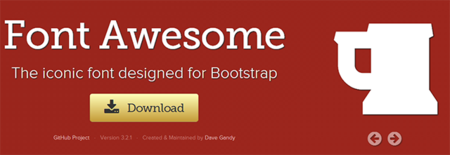
Cada vez más los diseñadores web queremos prescindir de las imágenes basadas en bits como png o jpg todo lo que podamos en favor de contenido vectorial y escalable. Con esta idea se ha creado Font Awesome: Iconos escalables para tu web con bootstrap.
Se trata de un proyecto para mediante el uso de la propiedad font-face de CSS3 y la etiqueta de HTML5 tener acceso a nada menos que 361 iconos totalmente escalables y en constante actualización con nuevos iconos.
Lo mejor es que a efectos del sistema funciona como si de una fuente tipográfica se tratara por lo que podemos cambiar su tamaño, su color, etc fácilmente desde CSS.
Los desarrolladores han cuidado hasta el más mínimo detalle y pata que la fuente no interfiera con posible lectores de pantallas de invidentes usan los llamados caracteres de seguridad que son una parte de la fuente tipográfica que no se usa para los símbolos y letras comunes.